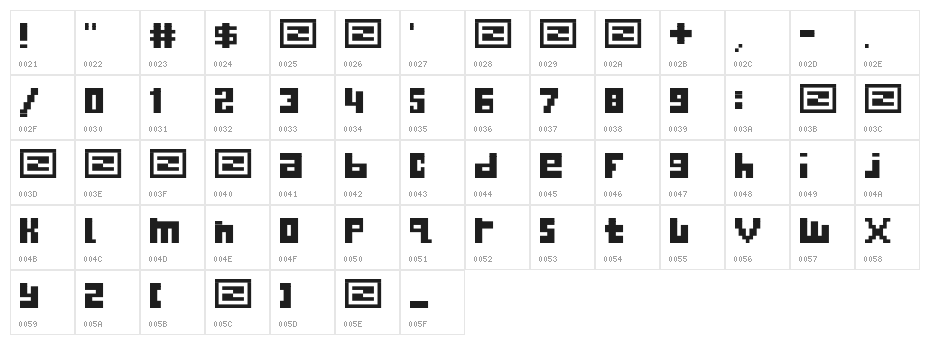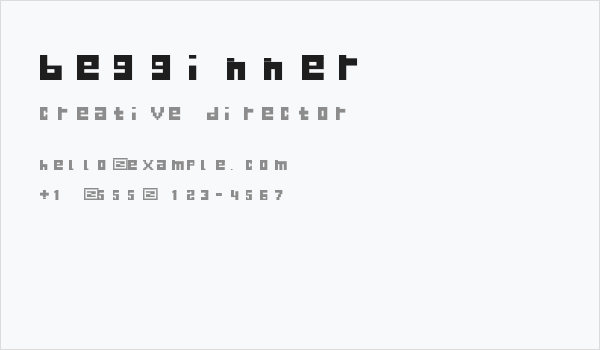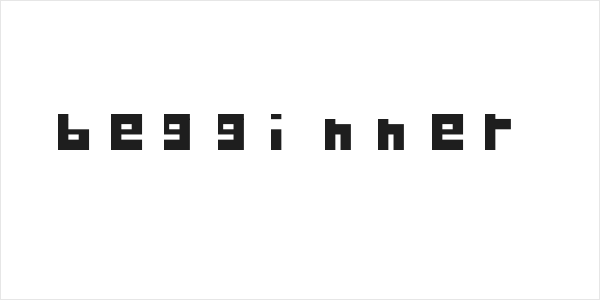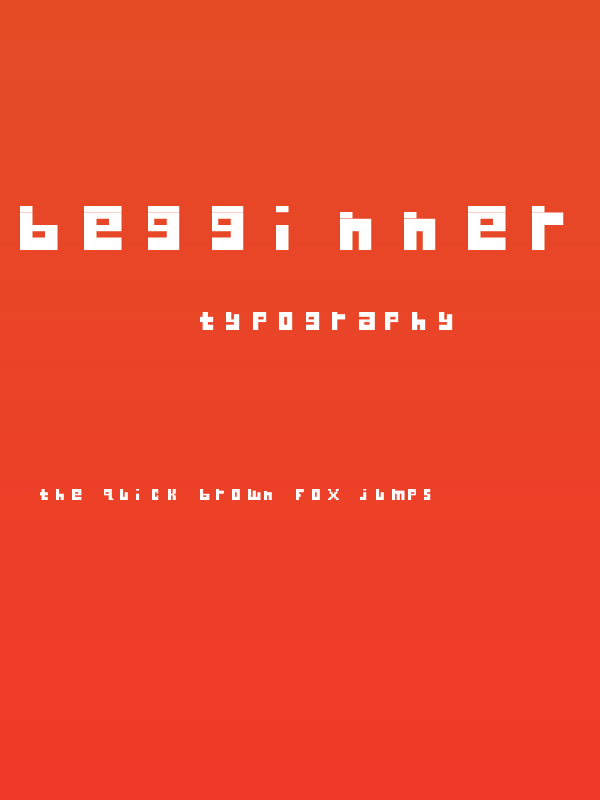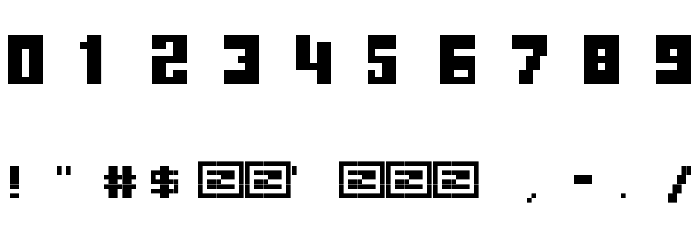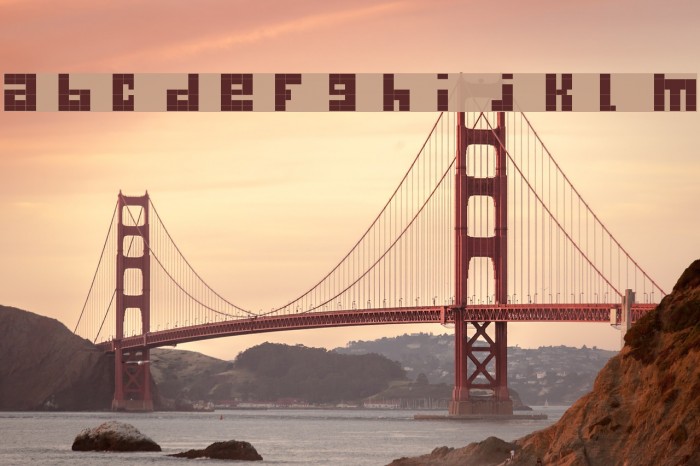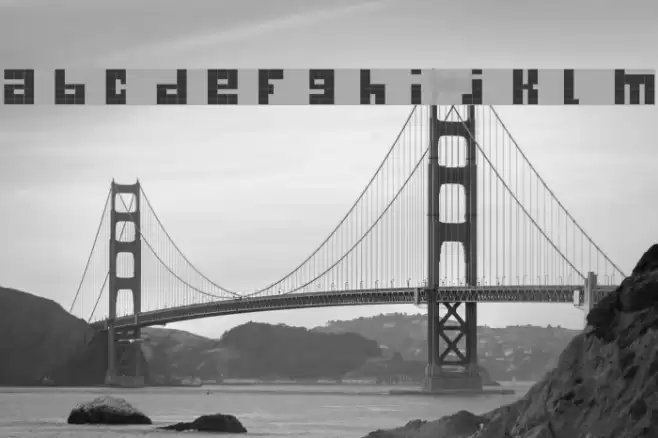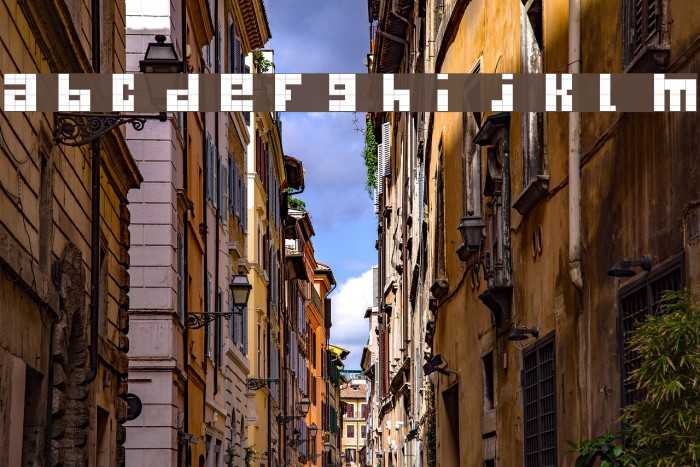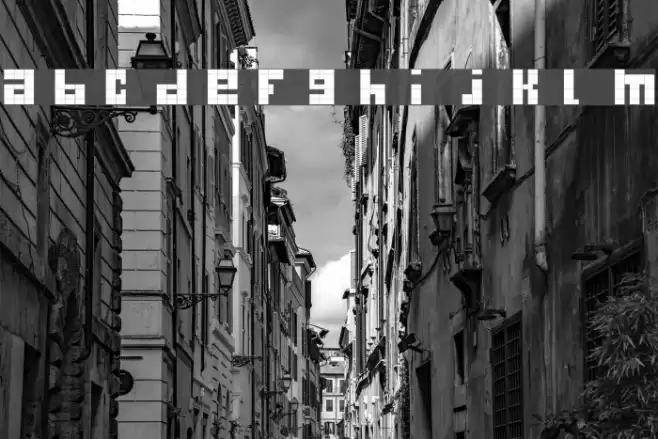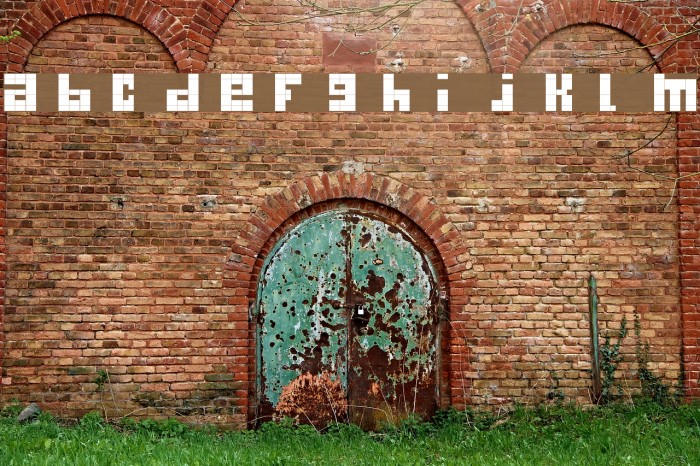
begginner Font
✎ Pixel
| Estilo general | Retro, Digital |
| Caso de uso | Headlines, Logos, Digital displays |
| Proyectos propuestos | Perfect for video game design, digital art, retro-themed posters, and tech-related branding. |